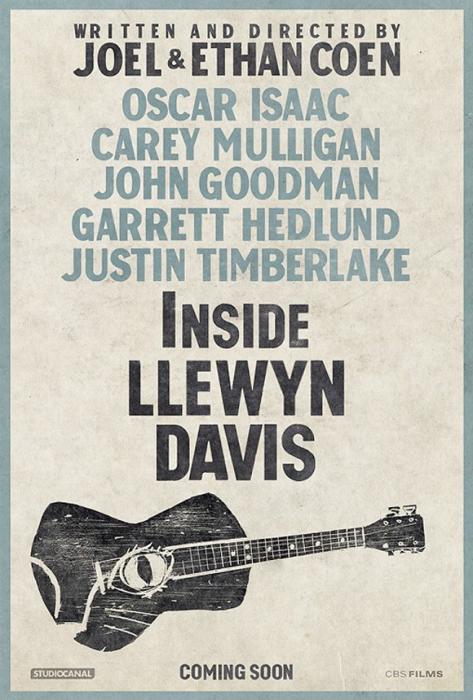
Inside Llewyn Davis
Wie heißt die Schrift mit der "Inside Llewyn Davis" geschrieben wurde und die mit der die Namen der Schauspieler geschrieben wurde. :-)
Die der Namen heißt "Llewyndavis Regular". Gut, bringt uns auch nicht direkt weiter, aber vielleicht weiß jemand, ob man zu dem Webfont auf http://insidellewyndavis.de noch mehr Infos bekommt …
Die Schrift der Schauspieler heißt "Llewyn Davis"!
Der Titelschriftzug ist in einer anderen Schrift gesetzt ...
Ähnlich wäre die Franklin Gothic (wenn diese nicht sogar als Grundlage diente). Vielleicht hast Du die ja durch ältere Software-Pakete sogar schon auf Deinem Rechner?
Edit: Dieser ähneln wiederum die Karla oder Chivo (Narrow) welche legal kostenlos zu haben sind. :-) Wirken aber alle nicht ganz so »handgeschnitzt«.